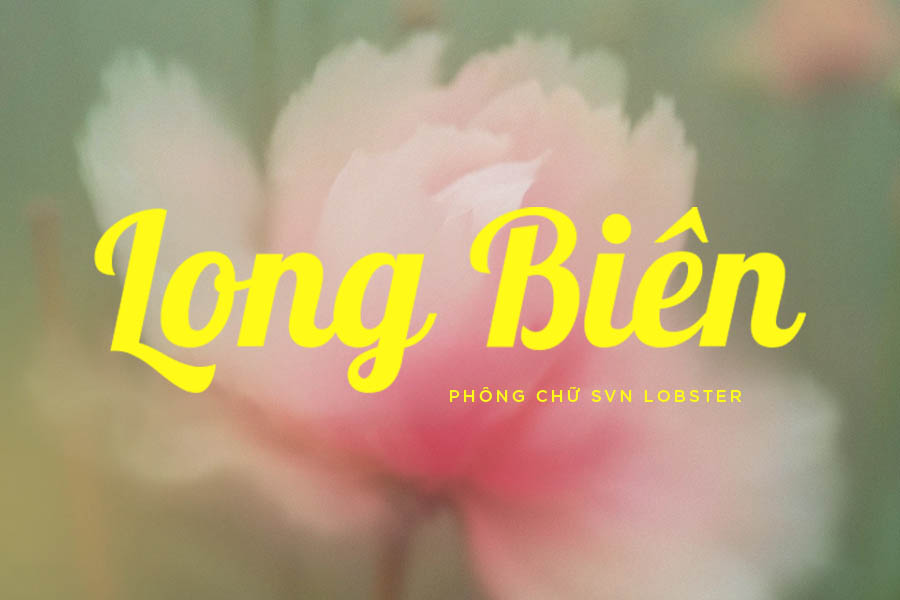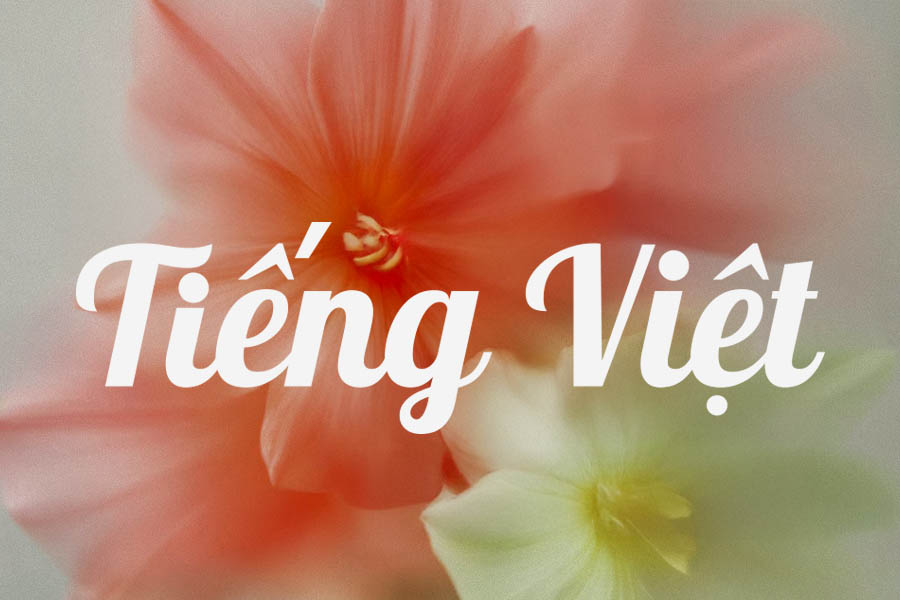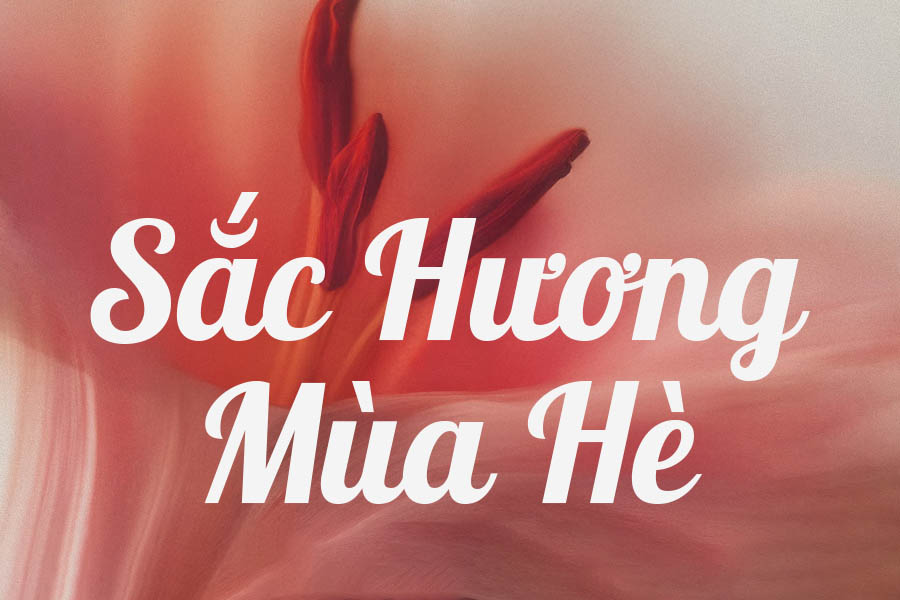
SVN Lobster – Font Chữ Viết Tay Đậm Cá Tính, Việt Hóa Chuẩn
Tác giả Pablo Impallari
Việt hóa Team SVN
Bạn đang tìm kiếm một font chữ viết tay đậm, nổi bật và giàu cảm xúc cho thiết kế logo, poster hay tiêu đề bắt mắt? SVN-Lobster chính là lựa chọn lý tưởng dành cho bạn. Đây là phiên bản Việt hóa chuẩn Unicode của font chữ nổi tiếng Lobster, được thiết kế bởi Pablo Impallari – một nhà thiết kế typeface đến từ Argentina, và Việt hóa bởi Công ty Cổ phần Phần mềm Sáng tạo (SVN).
Font Lobster là gì?
Lobster là một trong những font chữ script mạnh mẽ nổi tiếng toàn cầu nhờ sự kết hợp giữa nét viết tay tự nhiên và cấu trúc chữ đậm, sắc nét. Font sử dụng công nghệ OpenType thông minh để tự động chọn biến thể chữ cái phù hợp (ligatures), giúp văn bản luôn có nhịp điệu thị giác mượt mà và đồng đều. Đây là font script hiếm hoi vừa cá tính, vừa dễ đọc, được hàng triệu nhà thiết kế tin dùng trên toàn thế giới.
Điểm nổi bật của SVN-Lobster Việt hóa
Phiên bản SVN-Lobster Việt hóa không chỉ giữ nguyên tinh thần của bản gốc, mà còn được hoàn thiện đầy đủ dấu tiếng Việt, đảm bảo không lỗi ký tự, hiển thị đẹp trên mọi thiết kế. Font có độ đậm rõ rệt, chữ nối liền tinh tế, tạo cảm giác chắc chắn nhưng vẫn mềm mại – rất phù hợp cho các thiết kế cần điểm nhấn mạnh mẽ, hiện đại và truyền cảm.
Ứng dụng của font chữ SVN-Lobster
• Thiết kế logo cho quán cà phê, tiệm bánh, cửa hàng thủ công
• Menu nhà hàng, tiêu đề blog, poster quảng cáo
• Thiệp mời cưới, sự kiện, bìa sách nghệ thuật
• Typography trên mạng xã hội, story Instagram, banner thương hiệu
SVN-Lobster là sự kết hợp hoàn hảo giữa sự tự nhiên của nét viết taysức hút của phong cách đậm chất cá nhân – một lựa chọn không thể thiếu cho các dự án thiết kế đòi hỏi cá tính, sự nổi bật và cảm xúc rõ ràng.